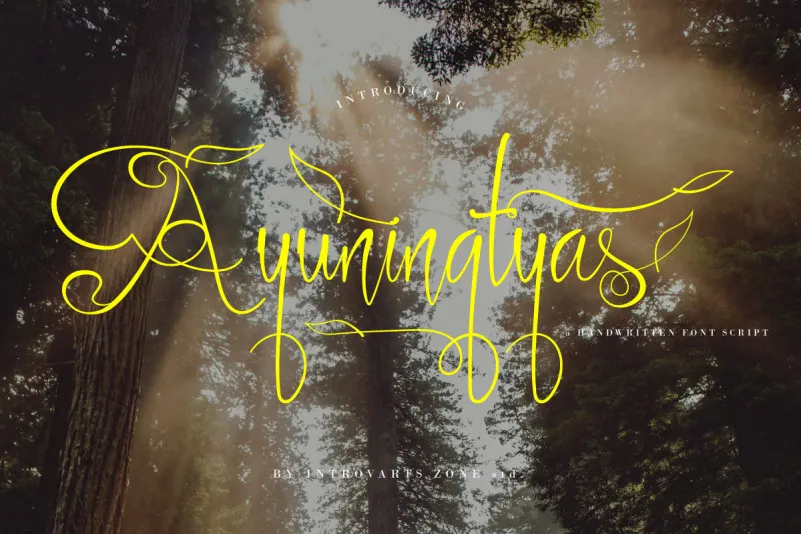
Ayuningtyas Script Font – Download Grátis
Introduzimos a Ayuningtyas Script Font, uma hermosa fuçna escrita à mão inspirada no nome do tipo de letra. O significado belo da palavra ayuningtyas é um forte elemento nesta fonte. A IntrovArtZone criou esta fuçna para variados fins, incluindo convites de casamento, design gráfico, design impressão, web design, logomarcas e outros. Ideal para dar um toque único aos teus projetos, a Ayuningtyas Script Font traz uma mistura única de elegância e personalização. Ela é perfeita para adicionar um toque original ao teu próximo projeto visual. Seja ele o design de logotipo do seu novo negócio ou até mesmo a criação daquela cartinha especial, ela está lá para tornar tudo mais especial. A Ayuningtyas Script Font não só é uma opção ideal para quem procura um estilo autêntico e criativo para seus projetos, mas também oferece flexibilidade. Pode-se usar esta fuçna em qualquer projeto que exija estilos elegantes e atemporais, seja ela impressa ou digital. Experimente a Ayuningtyas Script Font hoje e veja como ela pode transformar os teus projetos de design visual.